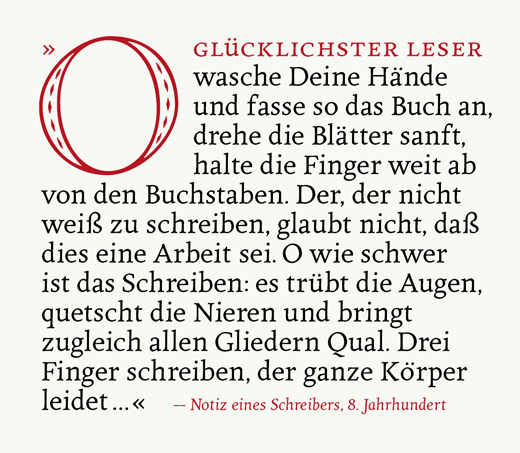
Werfen wir die Handschrift auf den Müll der Geschichte!
Professorin Anne Trubek plädiert in der NZZ dafür, die Handschrift »auf den Müllhaufen der Geschichte« zu werfen und keine Kinder mehr damit zu behelligen. »Die Handschrift ist nur ein winziger Funke in der Geschichte des Schreibens, und es ist Zeit, diese unnatürliche Art, Buchstaben zu formen, endlich abzuschaffen wie zuvor die Tontafeln, die Rauchzeichen und andere obskure Techniken.«
Weiß noch nicht, was ich davon halten soll … :twisted:
Ein schöner Abriss über die Geschichte des Schreibens.
Als Kind habe ich mich wirklich in die Handschrift-Formen reingelebt – das Versal-H wie ich es gelernt habe, hatte eine großartige Form, auch das X war eine Herausforderung, aber wenn's gelang, war ich ziemlich glücklich :) – summa summarum: ich habe Schreiben gemocht, und ich denke neben den bunten, geometrischen Bauklötzen im Kindergarten und meiner Buntstift-Sammlung hat mich das durchaus früh visuell geprägt (ohne dem jetzt gleich *zu* viel Bedeutung zumessen zu wollen).
Heute brauche ich im Alltag Handschrift defacto einfach nicht mehr, und meine ist ungeübt und schrecklich anzusehen, ich bin langsam und konzentriere mich dadurch mehr auf die Schrift statt auf den Inhalt. Schade? Aus nostalgischen Gründen ja, auf jeden Fall, aus praktischen Gründen für mich eher nicht.
Also weiterhin Schreiben unterrichten als Formenlehre, als Training zum Wahrnehmen und Wiedergeben von Formen? Vielleicht erweitert auf visuelle Zeichensysteme?
... es ist Zeit, diese unnatürliche Art, Buchstaben zu formen, endlich abzuschaffen ...
Manche Leute haben vieleicht Ideen ... Nein! :oops:
Ah, ich weiß jetzt. Die Dame geht auf das Symptom los und nicht den Erreger. Es müsste eigentlich eine Anklage gegen das pädagogische System sein, das Kindern das Schreiben lernen vermiest. Stattdessen greift sie das Schreibsystem an sich an. Was kommt demzufolge als nächstes? Werfen wir das Kopfrechnen auf den Müll, weil wir eh die Ti30 im Scheckkartenformat haben?
Okay, Thema verfehlt.
Peinlich, dass die NZZ einen solchen Quatsch publiziert ...
Ich finde die Argumentation der »Professorin« geradezu grotesk: Handschrift soll eine unnatürliche Art des Schreibens sein. Ja Himmelherrgott, welche Art des Schreibens ist denn natürlich? Schreiben ist eine höhere Kulturtechnik, niemand kommt mit dieser Fertigkeit auf die Welt. Genauso gut könnte man dafür votieren, das Geige spielen abschaffen zu wollen. Ist schliesslich eine äusserst unnatürliche Bewegung.
Schreiben fördert die Konzentrationsfähigkeit, die Feinmotorik, und verbindet in idealer Weise Kopf, Herz und Hand. Pestalozzi lässt grüssen, Frederic Vester ebenfalls.
Eine schöne Handschrift erreicht nur, wer immer wieder, täglich, übt. Dazu braucht es so altmodische Tugenden wie Fleiss, Ausdauer, Disziplin. Möglich, dass dies in der Frau Professorin unverarbeitete Traumata weckt, ich weiss es nicht. Ich persönlich schätze die Handschrift als ein persönliches Mittel der Kommunikation.
... kam mir auch so vor wie das Wehklagen einer hysterischen Mutter - mit ordentlich Pseudoradikalität und Kulturgeschichte garniert, damit nicht aussieht wie das Wehklagen einer hysterischen Mutter.
Liebe fellow-typomanen, erst der ikea katalog mit der verdana und jetzt die NZZ mit der wiedergeborene esther villar. es sind harte zeiten und da müssen wir durch. müssen wir? nein kollegen, wir müssen gar nicht, wir dürfen sogar nicht. wir dürfen nicht so naiv sein, auf den trick von frau prof. reinzufallen.
sie möchte, und wer von uns kann es ihr übelnehmen, ihre bücher auch in deutschland verkaufen. ob sich in usa jemand für sie interessiert weiß ich nicht. ist auch egal. das medium (siehe unten) ist immer noch der botschaft. wer werfe das erste steinchen in den typomanen-pool und schaut mal nach ob sich in der schweiz oder in der brd eine didaktik-tsunami entwickelt.
eine diskussion über ein thema das gar keins ist. inhaltlich quasi wissenschaftlicher dünnschiss. aber so bringt man/frau sich ins gespräch (bloß worüber) und die nzz leistet handdlangerdienste. ob frau prof demnächst in den brd talkshows die runde macht? wahrscheinlich. ich hoffe sie bekommt dann kompetente widersacher wie mein akademieprof gerrrit noordzij, der sie darüber aufklären könnte, welche verbrechen die schulen an unsere kinder verüben und was dann aus denen wird (pisa). mein tip: frau trubeck ignorieren. thread löschen... :huhu:
yeah, so geht man am besten mit meinungen um, die man nicht teilt.
zur sache: was spricht denn dagegen, kindern in der grundschule von anfang an blockschrift statt der verbundenen ausgangsschrift beizubringen? das wäre doch ein weg zu dem von anne trubek formulierten wunsch, dass handschrift kein krampf, sondern ein »Automatismus (…), der uns erlaubt, so schnell wie möglich zu denken« sein soll. 99% der erwachsenen, die ich kenne, schreiben ohnehin un- oder kaum verbundene buchstaben.
eine kleine stichprobe im kollegen- und bekanntenkreis hat gezeigt, dass kein zwingender zusammenhang zwischen der qualität der effektiv benutzten handschrift und der beherrschung der ausgangsschrift besteht. heißt: es gibt leute mit sauklaue, die mit kaum mühe eine ganz manierliche ausgangsschrift hinbekommen, und leute mit recht harmonischer, flüssiger handschrift, deren versuch, wie in der grundschule zu schreiben, ein totalausfall ist.
Ein guter Bekannter hat mich gebeten, für ihn hier einen Kommentar zu schreiben:
Ich habe einen Enkel (meinen ersten Enkel übrigens, inzwischen fast 19 Jahre alt), der auch Simon heißt und der dieselben Symptome zeigte (nur nicht ganz so dramatisch). Er konnte – obwohl ebenso intelligent wie seine 4 jüngeren Geschwister – das Gymnasium nicht besuchen wegen allgemein schlechter Noten. Die zu spät erkannte Ursache: Legasthenie (Leserechtschreibschwäche, LRS). Sowas läßt sich doch therapieren! Hat die Frau Prof. denn nie davon gehört? Bevor sie stattdessen gleich eine ganze Kulturtechnik über Bord werfen will??